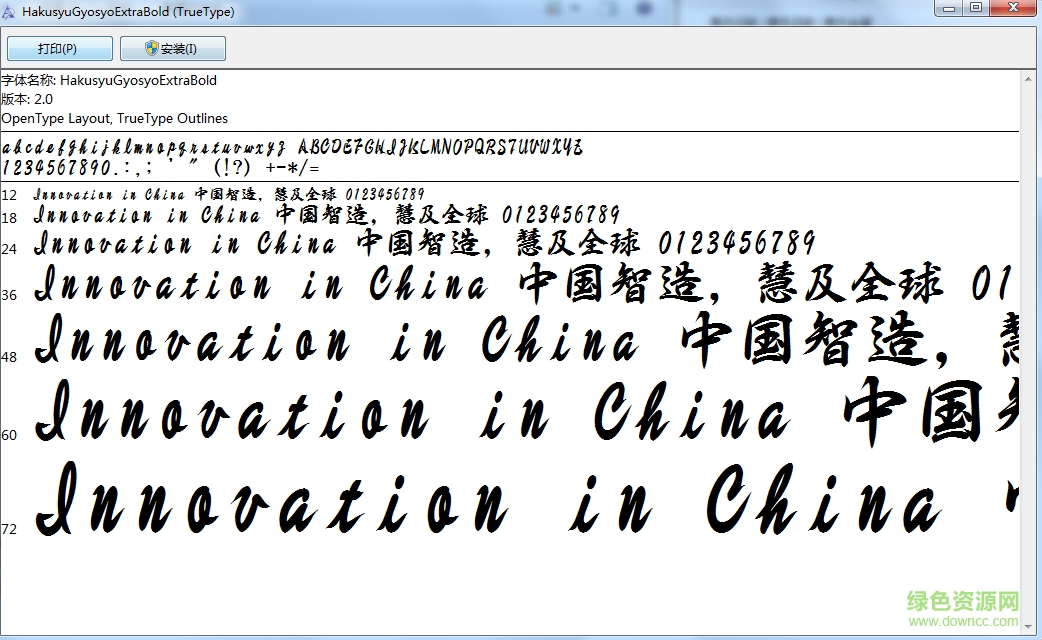
白舟極太行書(shū)
白舟極太行書(shū)白舟字體中的一款繁體行書(shū)字體,字跡連貫流暢,給你娟秀大氣之感,喜歡的朋友歡迎來(lái)綠色資源網(wǎng)下載!
白舟極太行書(shū)介紹
白舟極太行書(shū)是白舟字體系列中的藝術(shù)字體,以行書(shū)為綱,以繁體為精髓,字跡流暢娟秀,適合文字印刷、海報(bào)設(shè)計(jì)、廣告創(chuàng)意等行業(yè)。
極太行書(shū)